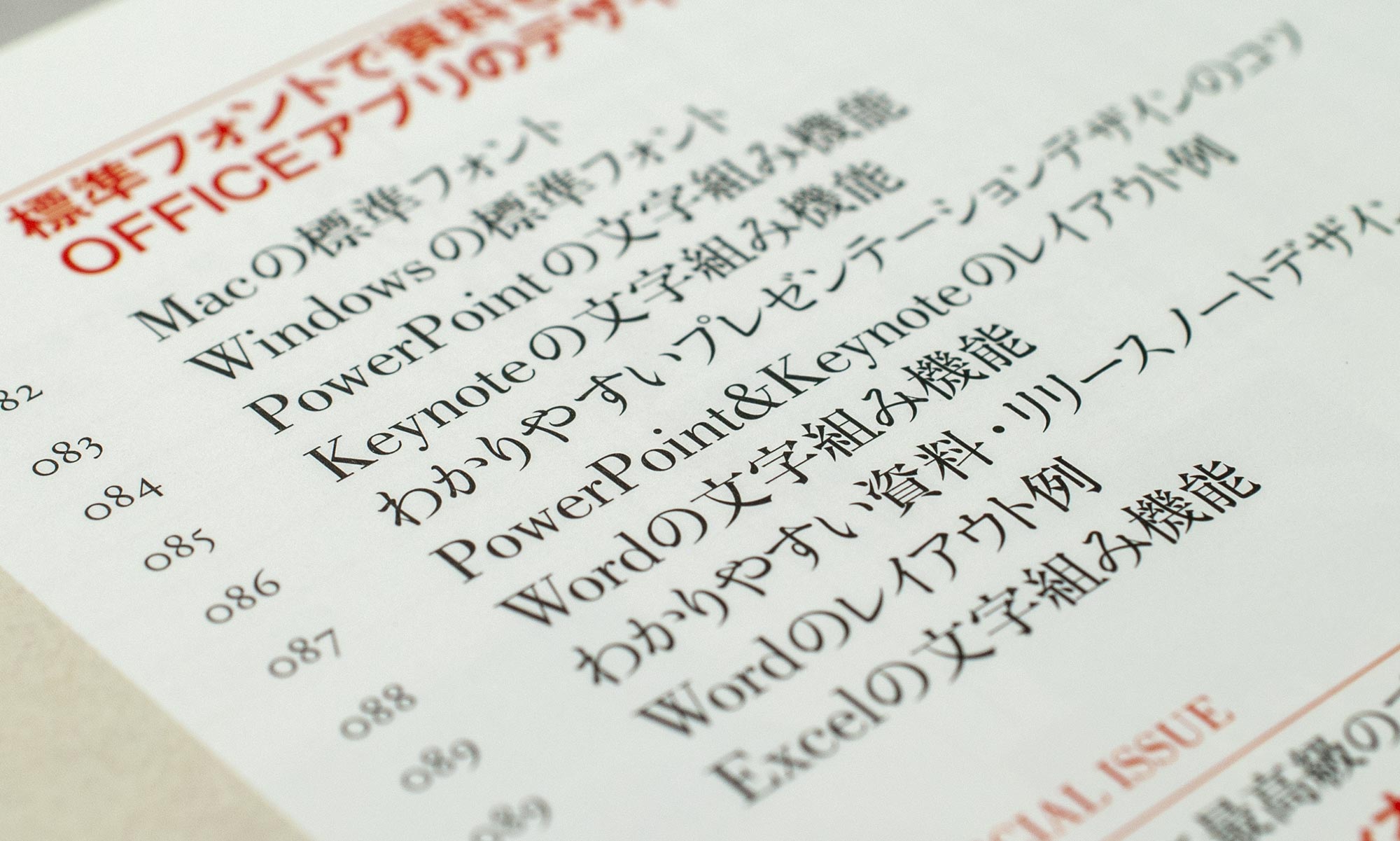
Lateinische Buchstaben im japanischen Text
Alleinstehende Ortsbezeichnungen, Produktnamen oder Satzarbeiten komplett in Englisch sind nicht das, womit die japanischen Setzer Probleme hätten. Es sind lateinische Buchstaben im japanischen Text, die sensible Typografen manchmal zum Wahnsinn treiben.
Alphabet im japanischen Text
Die Mühsal japanischer Typografen
So lautet auch der Titel des theoretischen Teils meiner Diplomarbeit. Ich schrieb darin, dass das lateinische Alphabet unter den japanischen Typografen für ziemliche Verwirrung gesorgt und die Kommunikationslandschaft ziemlich durcheinander gebracht hat. Vielen Japanern ist es heutzutage zwar egal, was sie im Alltag zu sehen bekommen, aber manche Typografen zerbrechen sich täglich den Kopf darüber, wie sie das Alphabet im japanischen Text harmonisch setzen sollen. Diese Aufgabe ist viel sensibler als manche denken.
In den folgenden Beispielen versuche ich eine heikle Problematik in der japanischen Satzarbeit zu veranschaulichen, die bei jedem »gemischten« Satz mit lateinischen Buchstaben auftaucht. Da es kein Allheilmittel gegen dieses Problem gibt, müssen japanische Typografen mit ihm leben und für jeden einzelnen Fall eine eigene Lösung finden.
Grundlinie und Mittelachse
Die Ursache des Problems ist ganz simpel: lateinische Buchstaben sind an der Grundlinie, japanische Schriftzeichen sind an der Mittelachse ausgerichtet. Vor allem die Minuskeln (Kleinbuchstaben) mit Unterlängen zerstören die Ruhe im Satz. Auch beim senkrechten Satz taucht dieses Problem auf, aber für europäische Augen ist vertikaler Textfluss ungewohnt, daher beschränke ich mich hier auf Beispiele in der gewohnten horizontalen Schreibrichtung.
Japanische und europäische Typography: Mittelachse und Grundlinie
Analyse zweier Welten, die gar nicht zueinander passen.
Es geht um den optischen Ausgleich zweier unterschiedlicher Schriftsysteme. Die Bedeutung des Beispieltextes spielt keine Rolle. Lateinische Buchstaben können überall im japanischen Text gesetzt werden, es gibt hierfür keine typische Stelle. Als Beispiele habe ich drei einfache Wörter in lateinischen Buchstaben ausgesucht, die sich jedoch in ihrer Optik voneinander stark unterscheiden: »Typography« mit fünf Unterlängen, »communication« ohne Ober- und Unterlänge und »TYPOGRAPHY« in Versalien.
Merkmale der japanischen und europäischen Schriftsysteme
Wörter in Silhouetten. Der Unterschied zwischen den beiden Schriftsystemen ist deutlich erkennbar. Im Japanischen ist die Mittelachse quasi die Symmetrieachse der Schriftzeichen und Ihr Textbild bleibt relativ homogen, während die Bilder der lateinischen Buchstaben je nach ihrer Kombination im Wort sehr unterschiedlich ausfallen.
Wenn lateinische Buchstaben im japanischen Text gesetzt werden
An diesen Konturen ist deutlich zu erkennen, wie sich fremde Buchstaben im japanischen Text einfügen. Kleinbuchstaben vertragen sich besonders schlecht mit Kanji.
Jetzt werfe ich noch kurz einen Blick auf die japanischen Fonts.
Beispieltext mit Kanji und Hiragana
Japanischer Text: Sechs Kanji und fünf Hiragana bilden den japanischen Beispieltext. Schrift: Ryumin Medium
Lateinische Buchstaben eines japanischen Fonts
Japanische Typedesigner sind sich der Problematik der lateinischen Buchstaben seit langem bewusst und haben sich bereits etwas einfallen lassen – sie haben die Unterlänge einfach verkürzt :^)
Japanische Schriftzeichen und lateinische Buchstaben eines japanischen Fonts
Eine gute Idee? Alles mit demselben Font gesetzt (Ryumin Medium), sieht das Ganze so aus. Die neuen Buchstaben passen auf alle Fälle besser in die Zeile, aber sie sind, mit Verlaub, einfach hässlich. Außerdem sind sie schlecht oder gar nicht gekernt (zwischen T und y u.a.). Daher kommt der Einsatz solcher Buchstaben bei mir nicht in Frage.
Wie ich auch in »Japan und das Alphabet« geschrieben habe, sind lateinische Buchstaben in japanischen Fonts generell vernachlässigt und Grafikdesigner würden sie für ihre Arbeit nie einsetzen. Abgesehen davon verwende ich für meine Kunden prinzipiell keine lateinischen Buchstaben aus japanischen Fonts, sondern die Fonts, die in der Originalausgabe verwendet wurden, wenn z.B. Eigennamen oder Adressen unübersetzt auch in der japanischen Ausgabe in lateinischen Buchstaben erscheinen sollen (mehr dazu finden Sie unter »Schrift und Image«).
Die gemischte Zeile wird nun in drei Schritten optimiert:
Mikrotypografie auf Japanisch: lateinische Buchstaben ersetzen
Schritt 1Die »hässlichen« Buchstaben wurden ersetzt durch Adobe Garamond Regular. Ihre Schriftgröße »im Zeichen-Bedienfeld« ist dieselbe wie die des japanischen Fonts, wirken aber im Verhältnis etwas klein.
Mikrotypografie auf Japanisch: Größe der lateinischen Buchstaben anpassen
Schritt 2Garamond vergrößert. Schriftgröße und die Strichstärke der beiden Fonts sind jetzt optisch ausgeglichen. Aber die vielen Unterlängen springen heftig aus der Unterkante heraus und das Wort wirkt wie eingesunken.
Japanisch-freundlich: Antique Olive Light in Hiragino Kaku Gothic W3
Auch wenn sich die oben erwähnten drei Schritte zum optischen Ausgleich – Schrift für das lateinische Alphabet auswählen, ihre Schriftgröße anpassen und die Grundlinien versetzen – in der japanischen Version von InDesign sehr einfach voreinstellen lassen, kann sich der Setzer nicht hundertprozentig darauf verlassen, dass damit alle Probleme gebannt sind. Je mehr lateinische Buchstaben im japanischen Text erscheinen, umso öfter muss der Setzer die »Unglücksstellen« manuell korrigieren, damit die ohnehin auffälligen lateinischen Buchstaben im japanischen Text halbwegs unauffällig bleiben.